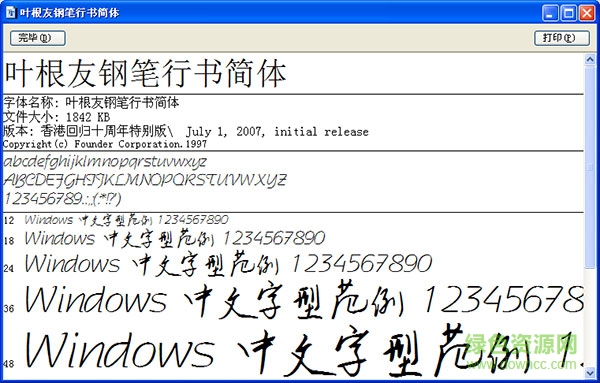
葉根友鋼筆行書簡(jiǎn)體是由中國書法奇人葉根友先生書寫,并在香港回歸十周年之際正式發(fā)布。 字體清晰自然,實(shí)用性強(qiáng),是書寫信件,BLOG等個(gè)性化字體的一不錯(cuò)的選擇。本字體供個(gè)人學(xué)習(xí)使用免費(fèi),商業(yè)使用需要授權(quán)。